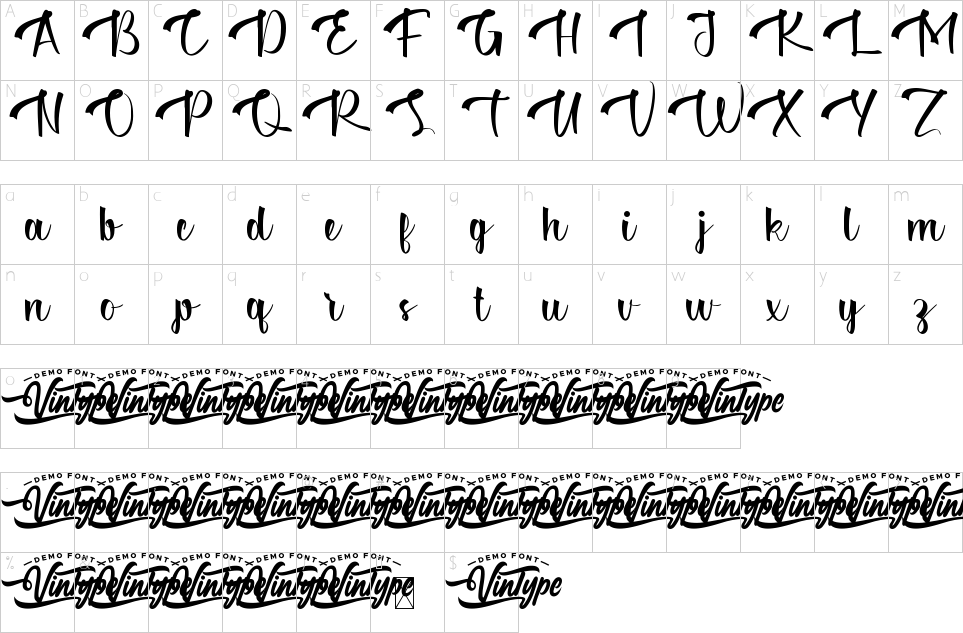
Aqui está uma descrição em português para a página de download da fonte ‘Mainaka Font | 1001 Free Fonts’: A fonte Mainaka é uma opção ótima para quem busca uma solução de fonte moderna e elegante para projetos digitais. Desenvolvida pela VinType, ela foi projetada para proporcionar textos agradáveis e legíveis, adequados para uso tanto em websites quanto em aplicativos de desktop. Com sua interface limpa e sua combinação única de linhas e espaçamentos regulares, a Mainaka atende perfeitamente aos requisitos de design para criar uma aparência harmônica em suas criações digitais. Baixe a Mainaka gratuitamente para Windows e Mac e experimente a tranquilidade de usar um design de fonte de qualidade sem precisar gastar dinheiro. Com mais de 3.794 downloads, a fonte Mainaka é uma escolha confiável para designers e criativos de todo o mundo.